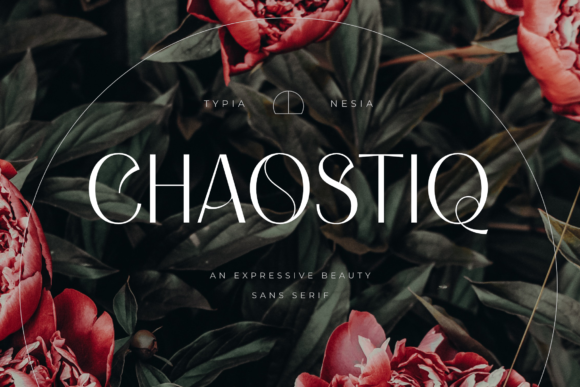
Chaostiq - элегантный и стильный шрифт Sans serif.
Хорошо читаемые символы и чистый, аккуратный стиль делают этот шрифт идеальным выбором для заголовков журналов, книг, упаковки товаров, баннеров и многого другого!